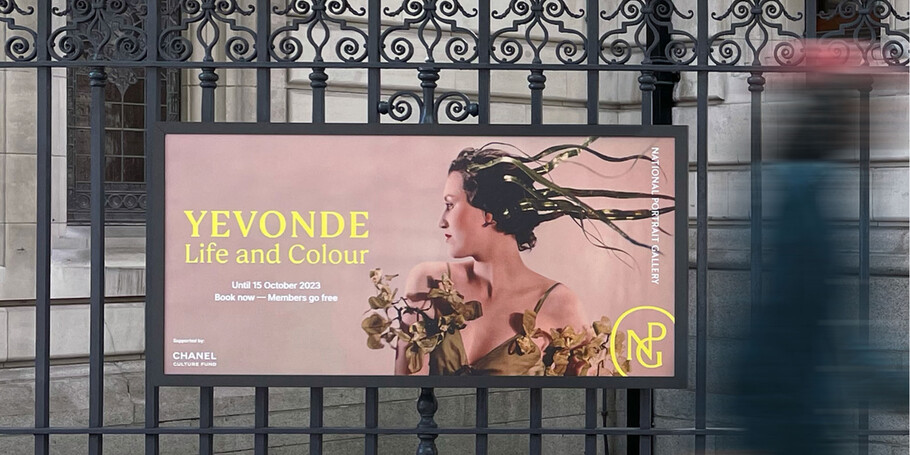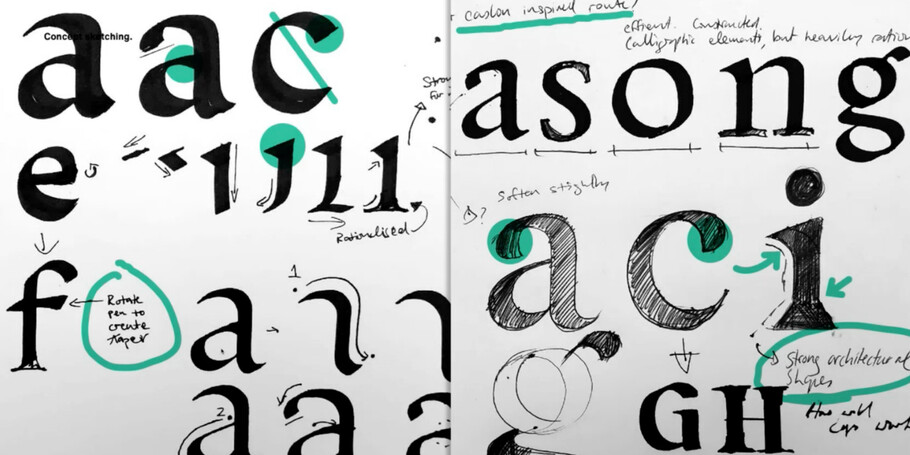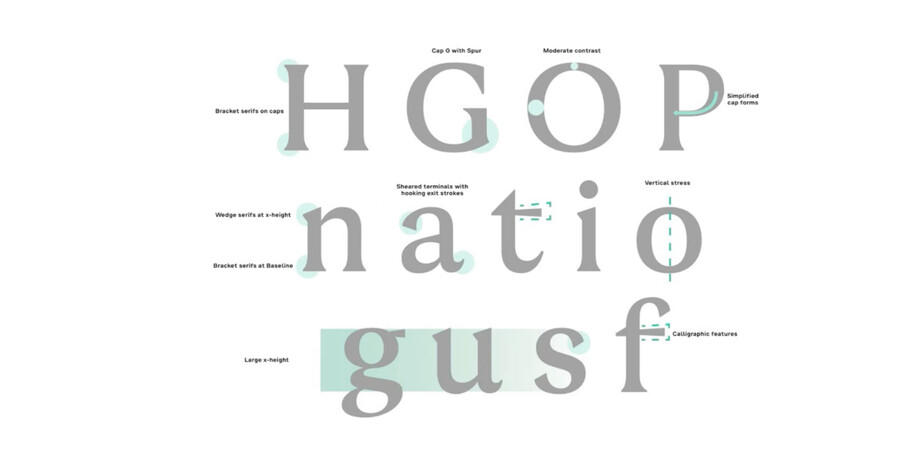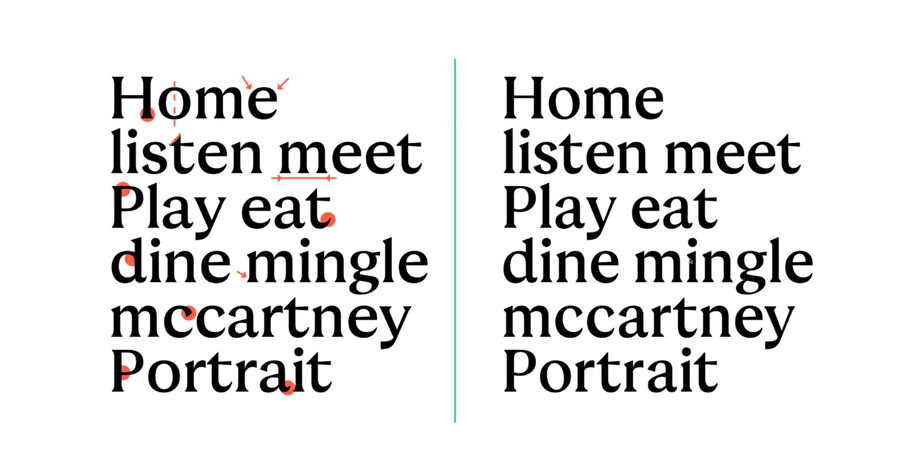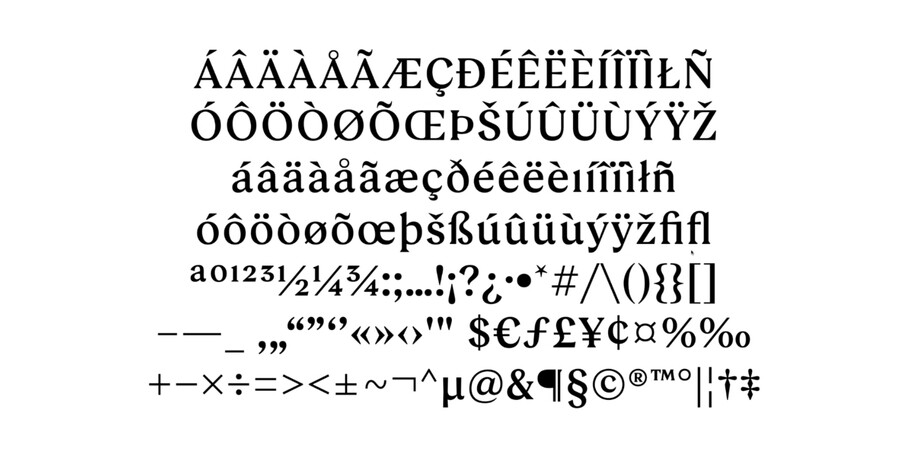
時代の変化とともにリブランドを選択した、ナショナルポートレートギャラリーのためのカスタム書体
「 Monotypeは、歴史あるナショナルポートレートギャラリーのためのクラシックと現代のスタイルの見事なバランスを保ったNPG Serifを開発しました。 」
EDIT 共同創設者 クリエイティブディレクター カーレン ヒューズ(Karen Hughes)
Monotypeは、ロンドンで最も期待されたリブランドの1つである、改装されたナショナルポートレートギャラリーのパートナーシップにEDIT の紹介のもと参加しました。このギャラリーは世界で最も象徴的で革新的な肖像画のいくつかを収蔵しています。改修作業は2020年に始まり、EDITの仲間たちはブランドを再構築し、パートナーであるBoardroom Consultingと共に変革的な戦略開発の依頼を受けました。
書体、タイポグラフィ、およびレタリングは、ブランディングプロジェクトの基盤です。イラストレーター兼レタリングアーティストのピーター・ホリッジ(Peter Horridge)と密に協力しながら、EDITはナショナルポートレートギャラリーの膨大で壮大、多様なコレクションを中心に据える新しいモノグラムと重なったロゴタイプシステムを開発しました。
ロゴをデザインするプロセスの初期段階は、タイポグラフィの研究と実験に時間を費やしました。これは、ブランドの声と個性を文字の形に具現化するためのプロセスです。ブランド戦略とアイデンティティが形成されるにつれて、Monotypeはフォントの発見プロセスをサポートし、ブランドのニーズに応えるためのクリエイティブな解決策を探りました。
アーカイブへの探求
由緒のあるクリエティブな機関であるナショナルポートレートギャラリーにはこのプロジェクトに役立つアーカイブが多く存在しました。EDITとナショナルポートレートギャラリーは観客調査の実施と美術館アーカイブの調査によって美術館の過去のアイデンティティを含む豊富な資料が提供されました。
Monotypeのエグゼクティブ・クリエイティブディレクターであるトム・フォーリー(Tom Foley)は、数え切れないほどの印刷物に没頭し、ポスターからパンフレット、さらには美術館の建築的な改装中に回収された石のモザイクまでからインスピレーションを引き出しました。「NPGのブランドアーカイブから豊富な参照資料にアクセスできることは、贈り物であり、過去からの挑戦状のようにも思えました」とトム・フォーリーは述べています。
「 NPGのブランドは年月を経て様々な表現をしてきましたし、最適な参照資料を見つけるのには時間がかかりました。どんな書体デザイナーであっても、数十年前のギャラリーのアーカイブから取捨選択する時間は惜しまなかったでしょう。 」
Monotype エグゼクティブ・クリエイティブディレクター トム・フォーリー
現代のクラシック
プロジェクトの初期段階で明らかになったのは、このブランドが歴史の重みを感じさせる書体を求めていることでした。それは、モザイクの中の文字と同様に、アール・ヌーヴォーに触発されたものを示唆していました。プロジェクトのブリーフを手に入れたトム・フォーリーは、アーカイブから一部を選び、素早くスケッチを開始しました。これらの手書きのアイデアから、ブランドの遺産研究の異なる側面からインスピレーションを得た5つのデザイン方向が導かれました。
環境はデザインを形作る
書体は孤立して存在するのではなく、さまざまな要素が加わりブラントのイメージとして発信されていきます。MonotypeとEDITは密に協力し、更新が行われるたびに、迅速に書体のアイデアを新しいブランドシステムに配置し、それが画像、ロックアップ、ロゴタイプとどのように機能するかを把握しました。そして、この書体があらゆる対照や色の異なる画像に対して際立つ必要があることが明らかになりました。これは多くのコーポレートフォントのデザインを決めることになりました。
テスト、テスト、テスト… そしてテスト
コンセプトの選択と到達は簡単です。書体デザインは芸術または工芸品です。アイデアや方向性を定義することは、ブラッシュアップの作業プロセスの一部であり、その後もさらなる工程が続きます。私たちは文字の形を厳格な基準に基づいて制作するプロフェッショナルであると自負しています。
EDITはまた、ブランドシステム内で書体をテストしており、ギャラリーの看板を担当するデザインエージェンシーも大きなスケールで書体をテストし、最適な結果となるよう注力しました。これらのすべてのテストは貴重なフィードバックを提供し、そのすべてが洗練プロセスに影響を与えました。
デザインにおいては、焦点を絞り込み、控えめなアプローチを取ります
NPGセリフは、1つのディスプレイ用と2つのテキスト用の合計3つのウェイトから成る小さなファミリーで構成されており、ギャラリーの物理的およびデジタルプラットフォームで最適な動作をするように最適化されたシンプルで堅牢なデザインです。
2023年6月22日、ナショナルポートレートギャラリーはグランドリニューアルを果たし、改装されたギャラリー、新しいアイデンティティ、そしてカスタムのタイプフェイスを訪れた来場者に披露しました。
「美しさ、持続性、柔軟性を具現化するビジュアルアイデンティティを創り出すことにフォーカスしました。ナショナルポートレートギャラリーの大切な歴史的ある作品とその現代のコレクション、展示プログラムを祝福するものです」とEDITのクリエイティブディレクター、カレン・ヒューズ(Karen Hughes)は述べています。「これを達成するために、私たちはまた、ブランドの遺産を保持しつつ、現代の世界で機能すブランドのためのコーポレートフォントが必要でした。Monotypeが制作したNPG Serifは、クラシックと現代のスタイルの見事なバランスを保ち、新鮮な印象を与えながらも、ナショナルポートレートギャラリーの豊かな歴史の視覚的なディテールに根ざしたデザインとなっています。」